Какво шрифт се използва за писане върху Vkontakte снимки
Днес, аз съм малко озадачен от намирането на подходящ кирилица, че би било възможно да се използва в Photoshop за съставяне на текст на една красива картина.
Сигурен съм, че много от вас знаят, че повечето от шрифтовете, които са инсталирани на компютъра по подразбиране, или тези, които са били записани отделно в колекцията не поддържа българските символи (букви).
шрифт например
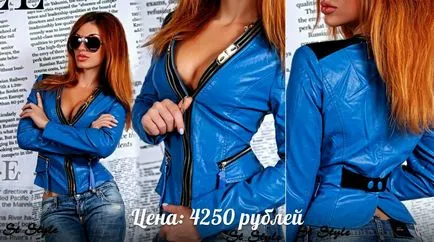
Тази картина е един от примерите на шрифта, който бих искал да се намери и да добавите към своя Photoshop CS6, но това не е проблем - да се намери, че не е толкова лесно.
Омар - шрифтът да пише върху снимките Vkontakte
Предполагам, че въпросът, който шрифт се използва в VK.com за надписи върху снимките, много хора се интересуват, така че реших да направя този преглед и да Омар шрифта в "Yandex Драйв" какво би било то да е възможно, за да изтеглите, ако е необходимо.
PS: Може би това е най-доброто от шрифтовете в подкрепа на българските букви!